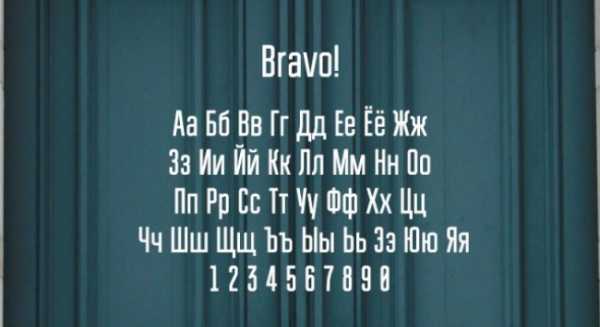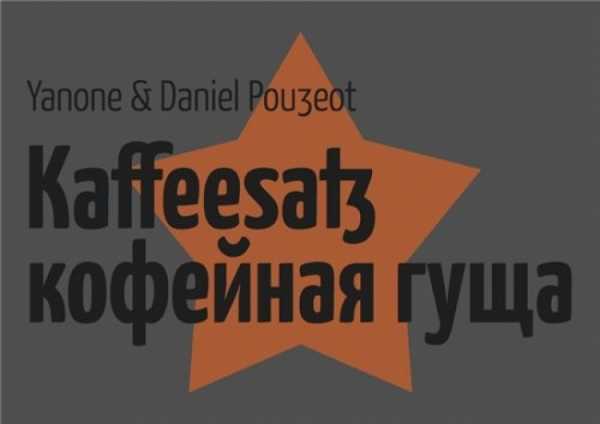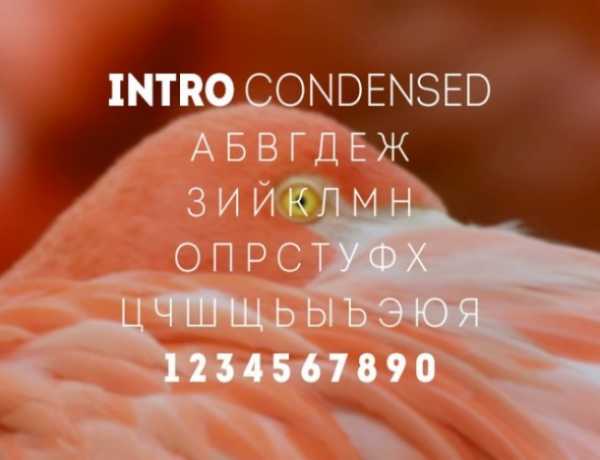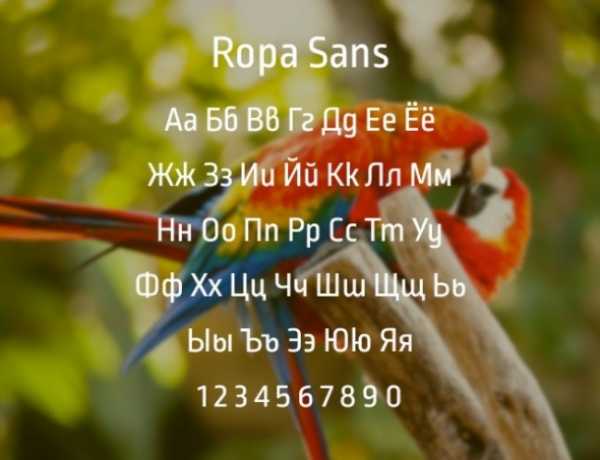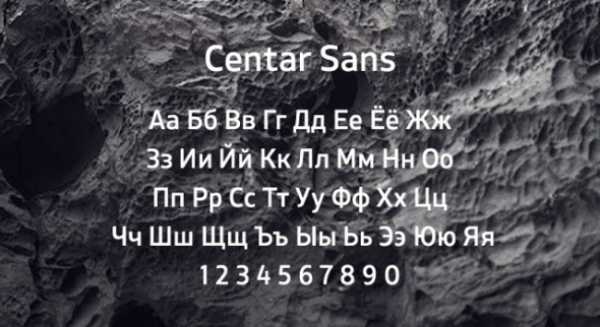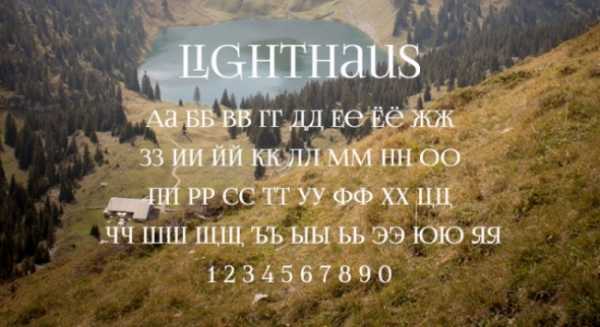
165 русских кириллических шрифтов
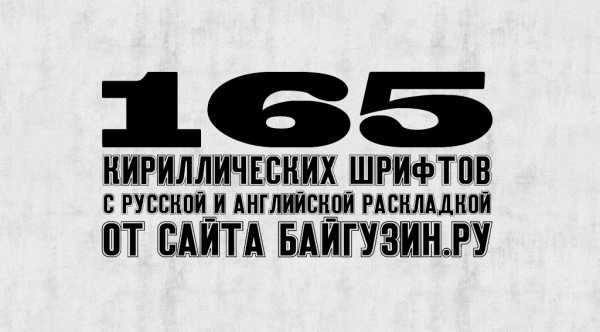
Добро. Наконец-то я доделал очередную сборку шрифтов. И она получилась самая большая на моем сайте. В сборке — 165 кириллических шрифтов с русской раскладкой. Пока не забыл сказать: в каждом шрифте имеется как русская раскладка, так и английская. Просто в прошлых сборках шрифтов я помню, что я проверял шрифт на фразе «Блог Эрика Байгузина», а там нет английских букв и из-за этого попадались шрифты, в которых нет английский раскладки.
Декоративный русский шрифт Acquest Script
СкачатьНаклонный декоративный русский Adine Kirnberg
СкачатьМодернисткий русский шрифт Agatha Modern
СкачатьКлассический декоративный шрифт Alexandra Script
СкачатьРусский декор-шрифт Allegretto Script Two
СкачатьШрифт Andantino script в русской раскладке
СкачатьКрасивый декоративный шрифт Angelica
СкачатьАрабский шрифт DS Arabic в русской раскладке
СкачатьШрифт Ariadna script с ярко выраженными заглавными
СкачатьРусский шрифт Arkhive, сделанный под старину
СкачатьАрт-шрифт ArtScript в русской раскладке
СкачатьЖирный декоратинвый шрифт Asessor
СкачатьКириллический наклонный шрифт Astra
СкачатьЕще один декоративный шрифт Aurora script
СкачатьШрифт Bickham Script One в кириллице
СкачатьВариация шрифта Bickham Script Three
СкачатьВариация шрифта Bickham Script Two
СкачатьКириллический шрифт Bolero script
СкачатьТолстый русский шрифт Boyarsky
СкачатьКаллиграфический русский шрифт Caligraph
СкачатьДекоративный русский шрифт Calligraphia One
СкачатьДекоративный русский шрифт Calligraphia Two
СкачатьАккуратный декоративный шрифт Cansellarist
СкачатьСтильный декор-шрифт Carolina
СкачатьДекоративный русский шрифт Cassandra
СкачатьРусский шрифт Ceremonious One с вензелями
СкачатьРусский шрифт Ceremonious Three с вензелями
СкачатьРусский шрифт Ceremonious Two с вензелями
СкачатьАккуратный каллиграфический шрифтChampignon Script
СкачатьРусский кириллический шрифт KB Chopin Script
СкачатьРусский шрифт Connetable
СкачатьШрифт Copyist с завитушками
СкачатьРукописный Corinthia в русской раскладке
СкачатьЖирный рукописный шрифт Corrida Bold
СкачатьЖирный рукописный шрифт Corrida Cyrillic
СкачатьНаклонный рукописный шрифт Cyrillic Brush
СкачатьСтрогий рукописный шрифт Cyrillic Ribbon
СкачатьРусский шрифт Cyrillic Chancellor
СкачатьКлассический Decor CTT в кириллице
СкачатьРусский неряшливый шрифт Dear Joe
СкачатьРукописный русский шрифт Demian
СкачатьИнтересный русский шрифт DisneyPark
СкачатьСтильный шрифт DomCasual
СкачатьПиксельный русский шрифт Dotf
СкачатьШрифт DrPoDecor с декоративными заглавными
СкачатьТонкий русский шрифт DS Note
СкачатьСимпатичный русский шрифт DS Rabbit Medium
СкачатьСамописный русский шрифт DS Eraser
СкачатьРусский шрифт DS Eraser2
СкачатьШрифт с вензелями Ekaterina Velikaya One
СкачатьШрифт с вензелями Ekaterina Velikaya Two
СкачатьКаллиграфический русский шрифт Elzevir
СкачатьАнглийский шрифт English Script на русском
СкачатьСтильный шрифт Epsilon CTT «от руки»
СкачатьСтильный пиксельный шрифт Epson
СкачатьКрасивый декор-шрифт Esenin Script One
СкачатьКрасивый декор-шрифт Esenin Script Two
СкачатьСимпатичный русский шрифт Favorit
Скачать«Неряшливый» шрифт FlowDian
СкачатьПриятный наклонный шрифт FreeHand
СкачатьСтильный шрифт Freestyle в русской раскладке
СкачатьСтрогий русский шрифт Geisha без засечек
СкачатьРусский жирный шрифт Globus
СкачатьШрифт Grinya в кириллической раскладке
СкачатьДекор шрифт Heather Script One в кириллице
СкачатьДекор шрифт Heather Script Two в кириллице
СкачатьДекор шрифт Heather Script в кириллице
СкачатьШрифт Heinrich Text
СкачатьНаклонный русский шрифт Hogarth Script
СкачатьКурсивный русский шрифт Hortensia
СкачатьЗаглавный шрифт Irina
СкачатьСимпатичный шрифт Isabella Decor
СкачатьСтильный «округлый» шрифт Joke
СкачатьКаллиграфический русский шрифт Karnac One
СкачатьЯпонский шрифт Keetano Gaijin в кириллице
Шрифт в японском стиле Keetano Katakana
Скачать«Сказочный» шрифт Kuritza
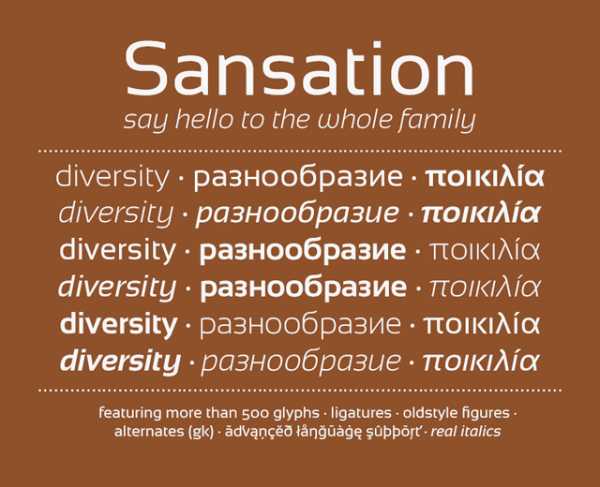
26. Ivan
27. Juan
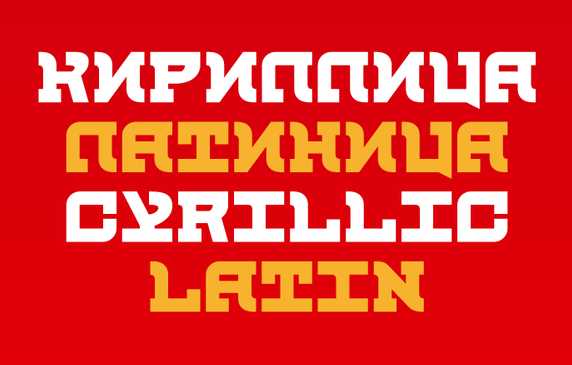
28. Archive
29. Aero Matics
30. Aero Matics Stencil
31. Hagin
32. Open Sans Condensed
33. Prosto
34. Intro
35. Charis SIL
36. Sports World
37. Metropolis
38. Ledger Regular (Google Web Font)
39. Forum (Google Web Font)
40. Roboto
41. Silverfake
42. Designosaur
43. Black & White
44. Webissimo
45. Tetra
46. Azoft
47. Minaeff
48. Web Serveroff
49. Miso
50. Demonic Tale